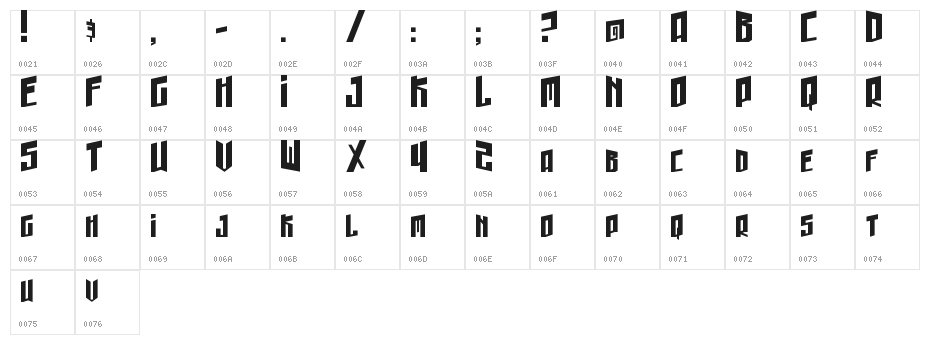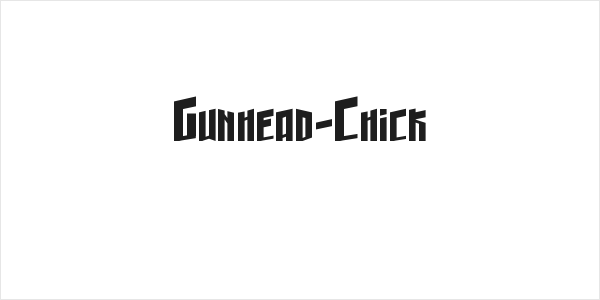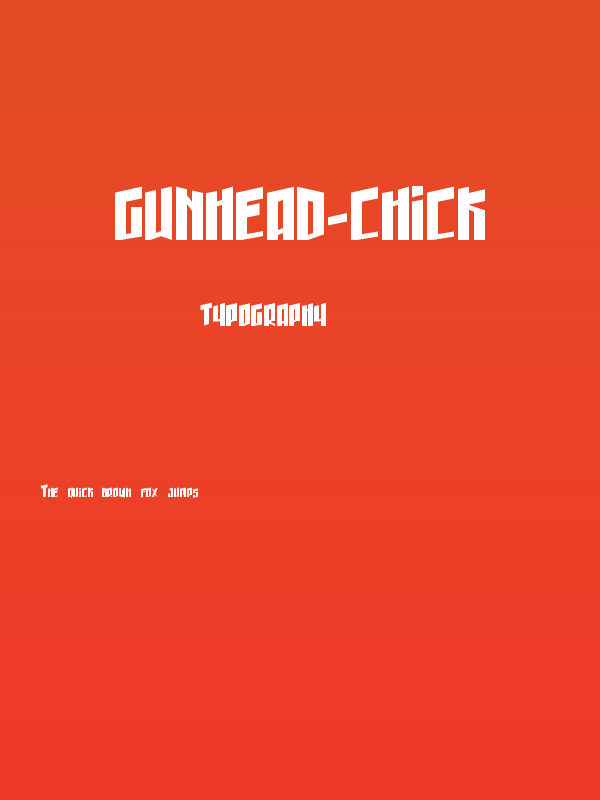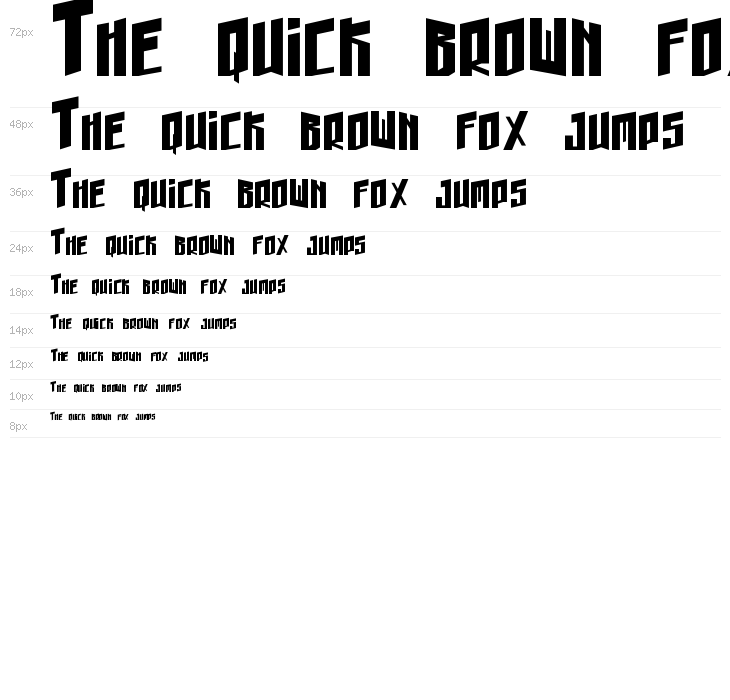
Gunhead-Chick Font
| Progetti proposti | Ideal for video game titles, movie posters, branding for tech companies, or any project needing a modern and bold typeface. |